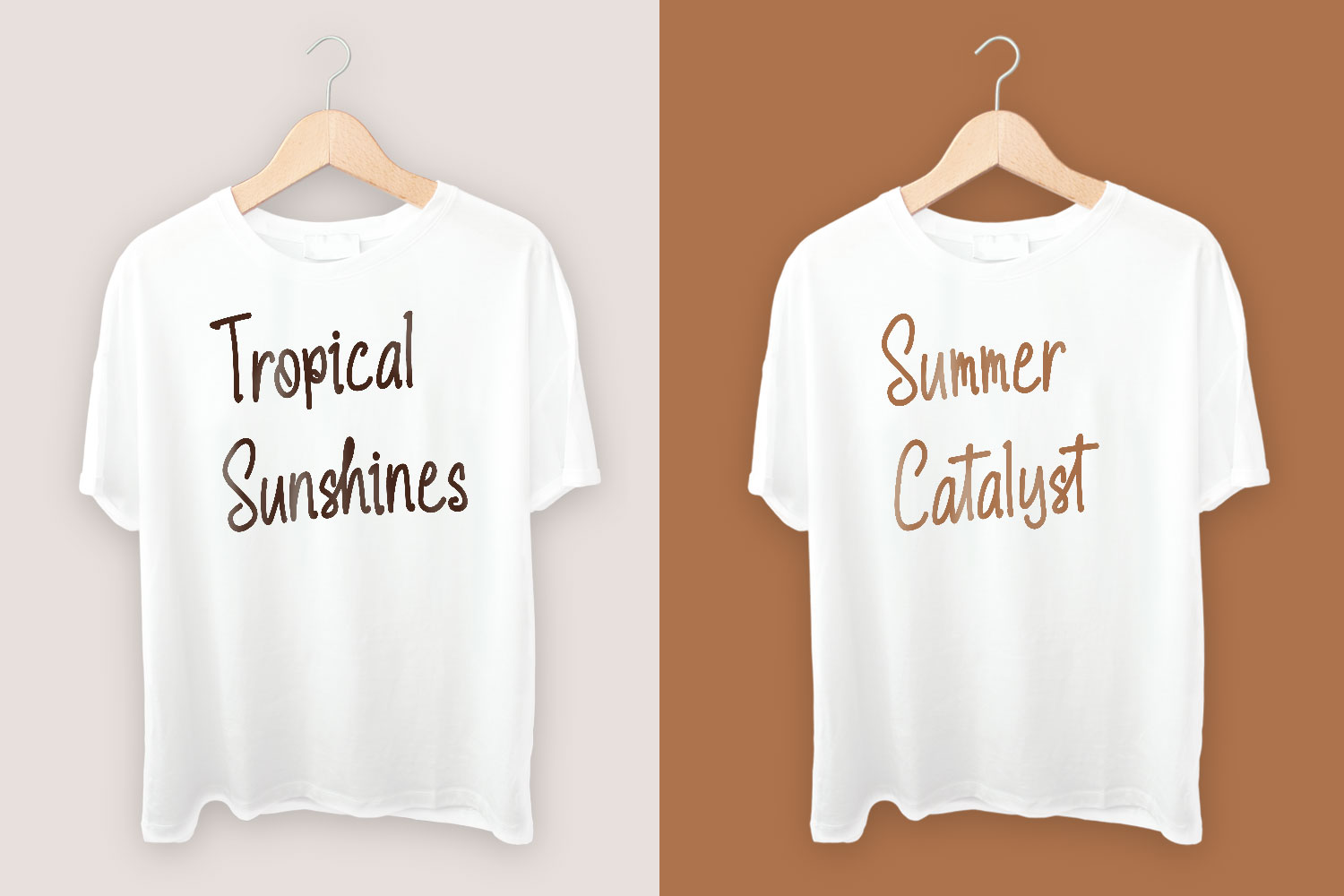
Ashford KeystoneFont是一款现代化的、专门用于虚拟矢量设计、数字婚礼宣传、博客、在线商店、社交媒体等印刷品的展示方,而印刷品可用于现场的产品服装、配件、包、别针、徽标、名片、水印和其他许多产品。Ashford KeystoneFont是一款现代化的、专门用于虚拟矢量设计的展示方,印刷品,如数字婚礼宣传、博客、网上商店、社交媒体,而印刷品可用于生产服装、配件、包、别针、徽标、名片、水印和其他许多领域。